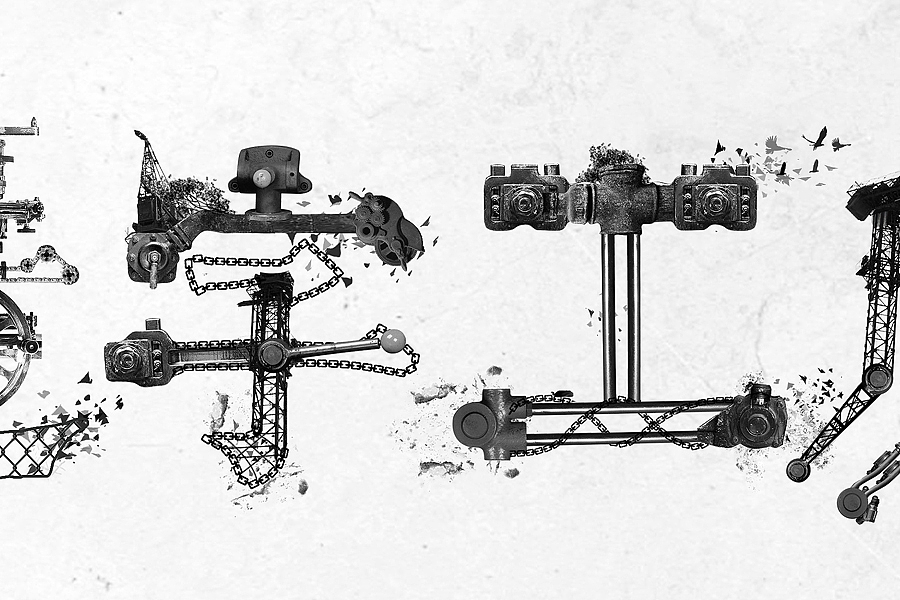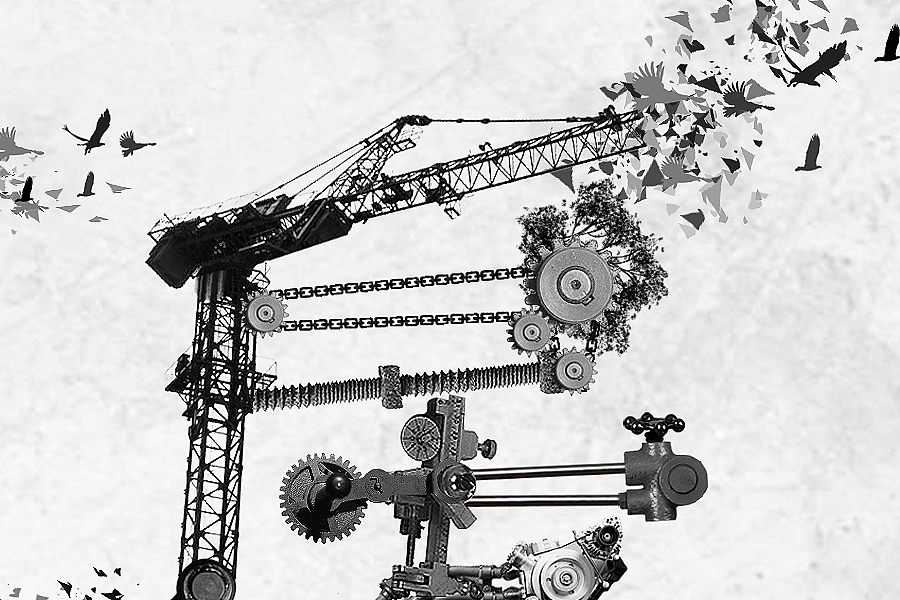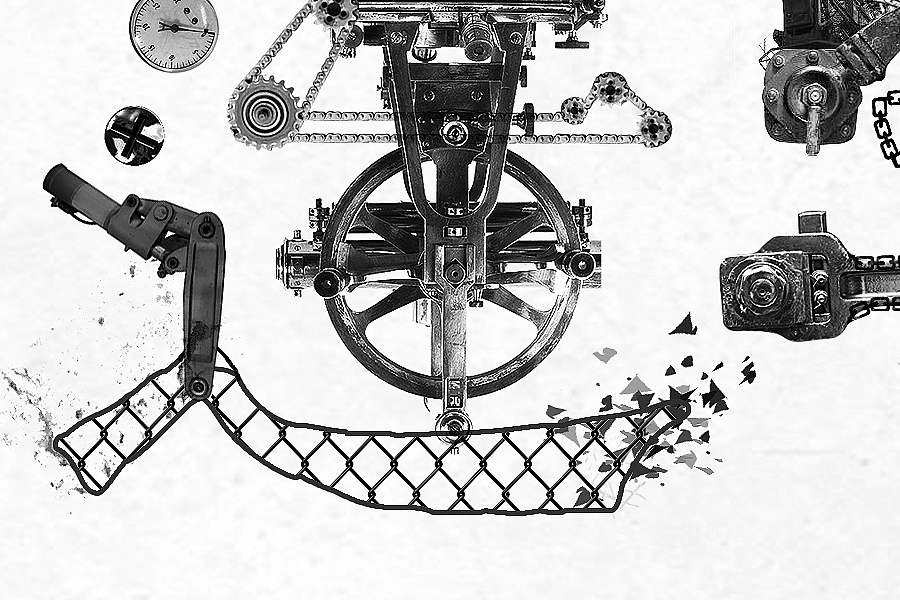
造字工房参赛作品!各种拼贴吧!
造字工房参赛作品!各种拼贴吧!(图ZMTM2Njk4NDg=) - 字体/字形 - 站酷设计师一纸油墨原创素材 - 站酷ZCOOL
造字工房参赛作品!各种拼贴吧!(图ZMTM2Njk4NDA=) - 字体/字形 - 站酷设计师一纸油墨原创素材 - 站酷ZCOOL
造字工房参赛作品!各种拼贴吧!(图ZMTM2Njk4NDQ=) - 字体/字形 - 站酷设计师一纸油墨原创素材 - 站酷ZCOOL
造字工房参赛作品!各种拼贴吧!(图ZMTM2Njk4NTY=) - 字体/字形 - 站酷设计师一纸油墨原创素材 - 站酷ZCOOL
造字工房参赛作品!各种拼贴吧!(图ZMTM2Njk4NjA=) - 字体/字形 - 站酷设计师一纸油墨原创素材 - 站酷ZCOOL